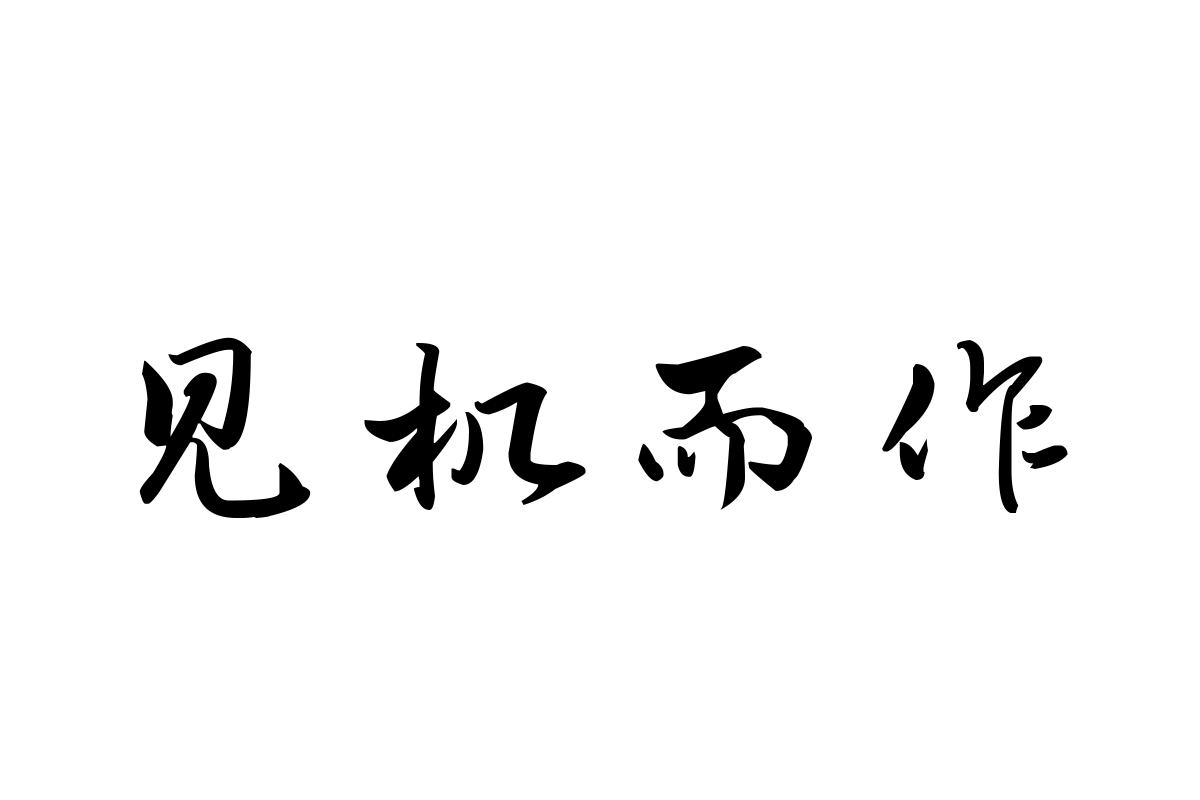
汉呈王天喜江湖体是一种书法字体,由著名书法家王天喜创作。这种字体具有独特的风格和特点,深受书法爱好者的喜爱。
1. 字形结构:汉呈王天喜江湖体字形结构独特,笔画流畅,线条粗犷有力。每个字的笔画都有独特的形状和弧度,使得整个字体看起来既有力度又有美感。
2. 风格特点:这种字体的风格特点是豪放、奔放,具有很强的个性和表现力。它能够很好地表达出作者的情感和思想,给人一种强烈的视觉冲击和艺术感染力。
3. 使用范围:汉呈王天喜江湖体主要用于书法创作,也可以用于其他需要表现豪放风格的场合。它的使用范围广泛,可以满足不同用户的需求。
4. 学习难度:由于这种字体的字形结构和风格特点较为复杂,所以学习起来有一定的难度。但是只要掌握了基本的笔画和结构,就可以写出漂亮的汉呈王天喜江湖体作品。
总的来说,汉呈王天喜江湖体是一种非常独特和有特色的书法字体,适合喜欢豪放风格的朋友学习和欣赏。